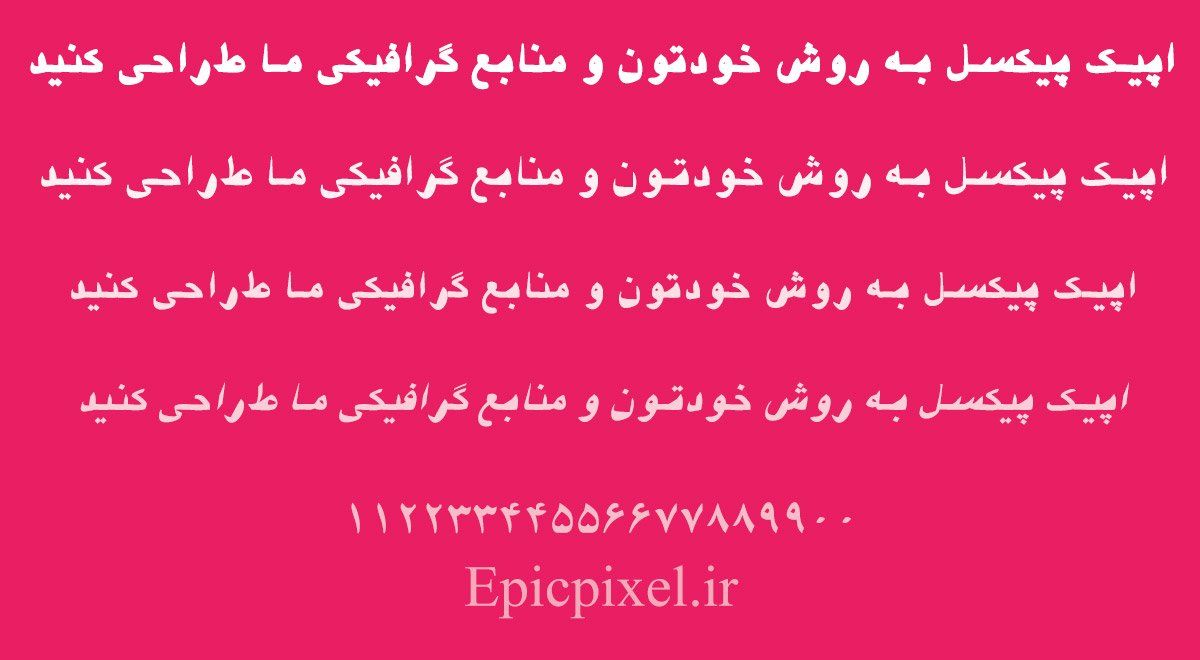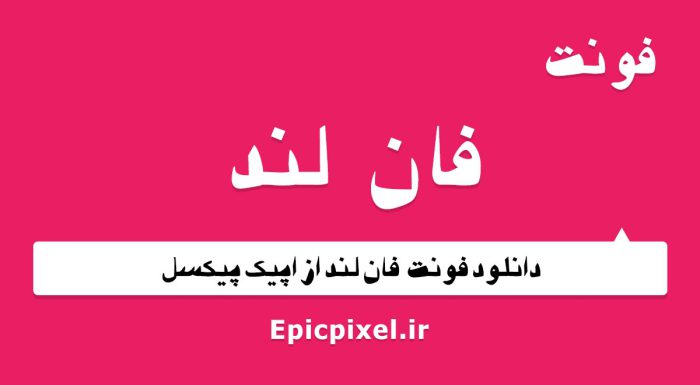
فونت فان لند فارسی
دانلود فونت funland فارسی Font فان لند رایگان |
| فونت | دانلود فونت فارسی فانلند جی بی رگولار Font jb funland Regular |
فان و بامزه…لول
چه فونتیه آخه!!!!!!!!!!بامزه بود ولی زیاد کاربردی نیست مگه برای کارهای فان